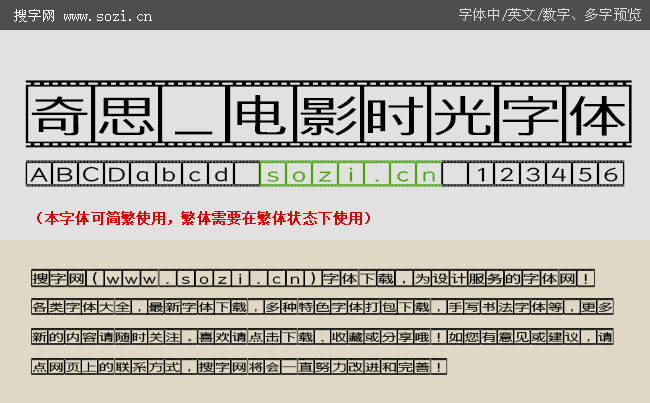
奇思_電影時(shí)光字體
搜字網(wǎng)提供一款奇思_電影時(shí)光字體手機(jī)中文藝術(shù)字體下載,奇思_電影時(shí)光字體是一款以黑體字為原形,為字體加上了電影膠片的圖案裝飾,適合在正式的場(chǎng)合來(lái)進(jìn)行使用,適合應(yīng)用于廣告設(shè)計(jì)、名片設(shè)計(jì)、包裝印刷、產(chǎn)品設(shè)計(jì)等應(yīng)用。